Best Free Inline Fonts
인라인 폰트는 폰트 중앙을 중심으로 공간을 만들어 강조를 해서 일반적인 문장에 자주 사용하지 않습니다.
하지만, 임팩트 있는 느낌을 표현할 때는 매우 유용하게 사용할 수 있기 때문에 디자인 작업 시 한 번쯤 활용해 보는 것도 좋습니다.
온라인에서 무료로 제공하는 인라인 폰트를 찾아보면 만족스럽지 못한 경우가 대부분입니다.
많은 폰트가 인라인 스타일을 가지고 있지만, 막상 사용해보면 원하는 느낌을 표현하는데 어려움을 겪을 수 있습니다.
이러한 불편을 해결하기 위해 디자이너들이 즐겨 사용하는 폰트를 찾아 공개합니다.
아래 리스트는 디자인에 사용할 수 있는 무료 온라인 인라인 스타일 폰트 모음입니다.
Mensch
Intro
Bender
Ostrich Sans
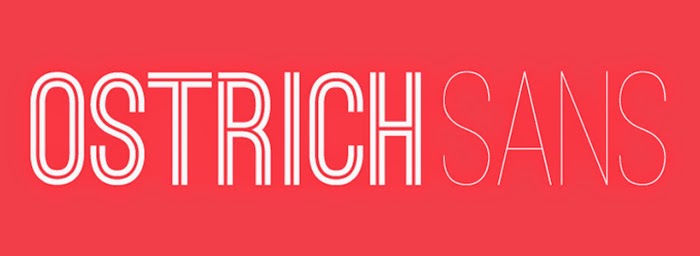
Conqueror Inline
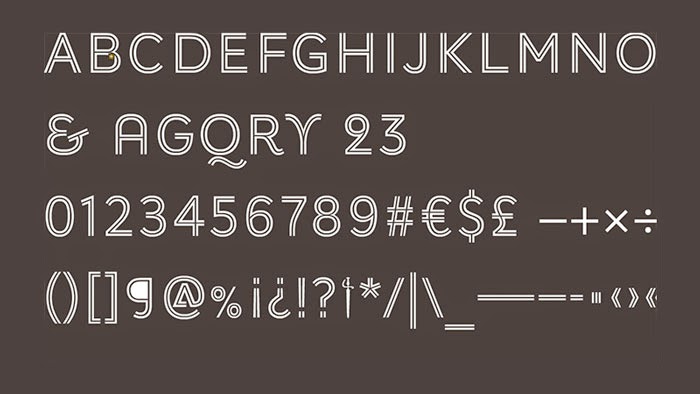
Rex
Blanch
Ribbon
Homestead
Lovelo